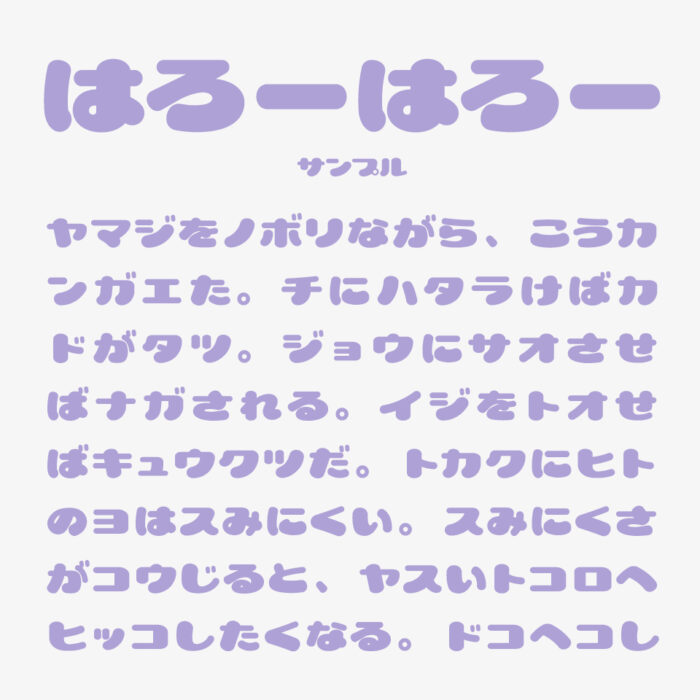
はろーはろー
はろーはろーフォントは、X上で配布しているグレイグラフィックスさんによるふっくらとした丸みとやさしさと柔らかさあふれるデザインフォントです。
線の太さが均一ではなく、文字全体がぽてっとしていて弾力感を思わせるシルエットが特徴で、80-90年代レトロ感のあるとっても可愛らしいデザインのフォントです。
収録文字は、ひらがな・カタカナが収録されています。